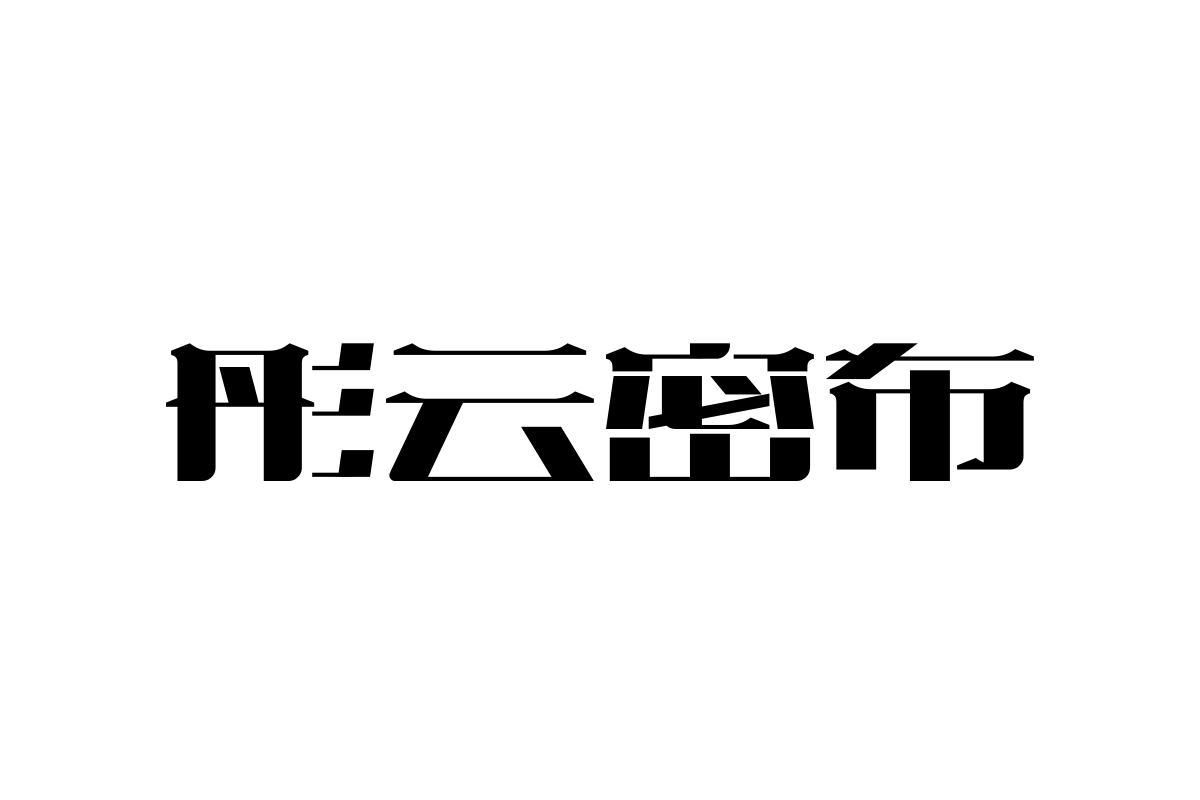
“上首星耀体”是一套具有独特风格的中文字体,由设计师精心打造。它采用了现代的设计元素,结合了传统的书法艺术,给人一种新颖、独特的视觉体验。
该字体的特点在于其字形的流畅性和结构的独特性。每个字符都经过精心设计,使得整个字体在视觉上呈现出一种动态美。同时,该字体还注重笔画的粗细变化,使得字体更加富有层次感和立体感。
此外,“上首星耀体”还具有一定的可读性。由于其字形简洁明了,易于阅读,因此在各种场合下都能得到广泛的应用。无论是在广告设计、网页设计还是其他印刷品中,都能展现出其独特的魅力。
总之,“上首星耀体”是一款非常优秀的中文字体,无论是从视觉效果还是实际应用的角度来看,都值得我们去尝试和欣赏。